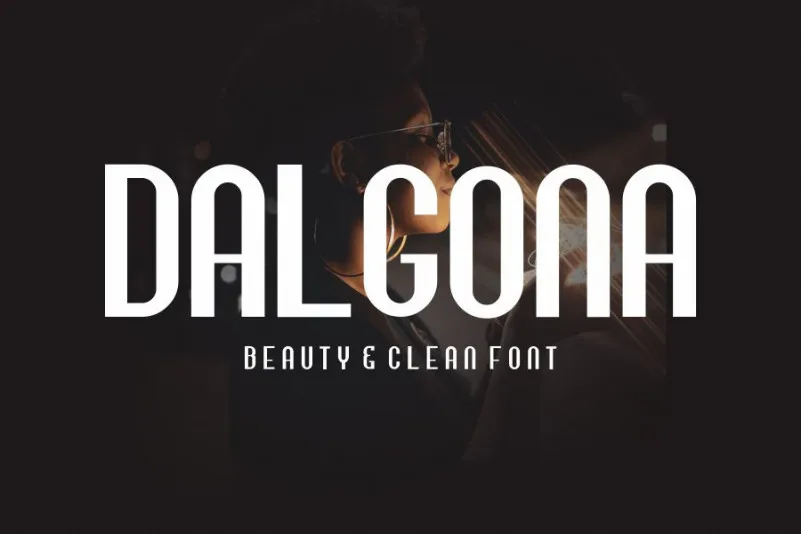
Dalgona Font – Download Grátis
A Dalgona Font é uma bela escolha para designers que buscam adicionar um toque de descontração e leveza a seus projetos visuais. Esta tipografia sans-serif, com seu estilo charmosamente hand-lettered, é perfeita para criar um impacto imediato em diversos tipos de trabalho gráfico. Desde logomarcas e cabeçalhos até designs de casamento e convites de festa, a Dalgona Font está preparada para encantar uma ampla gama de projetos. Seu formato elegante e sua facilidade na criação de texturas personalizadas tornam-na uma opção ideal não apenas para designers gráficos, mas também para aqueles que buscam imprimir em etiquetas ou criar assinaturas pessoais com um toque delicado. E mais do que isso, a Dalgona Font é uma excelente escolha para quem deseja dar uma pitada de irreverência ao seu trabalho, seja na criação de logotipos ou em outros elementos visuais, sem perder o grau de sofisticação e elegância necessários.
Designer: Maknastd